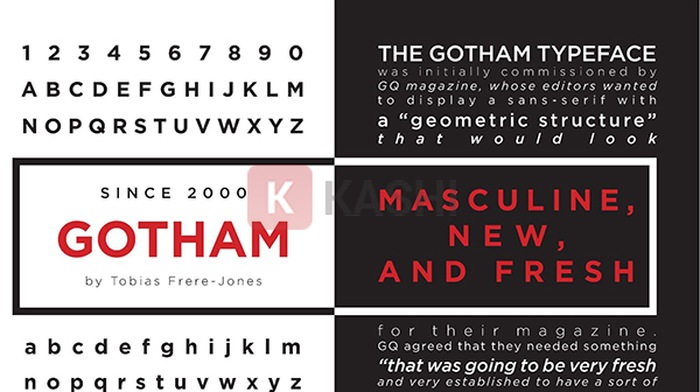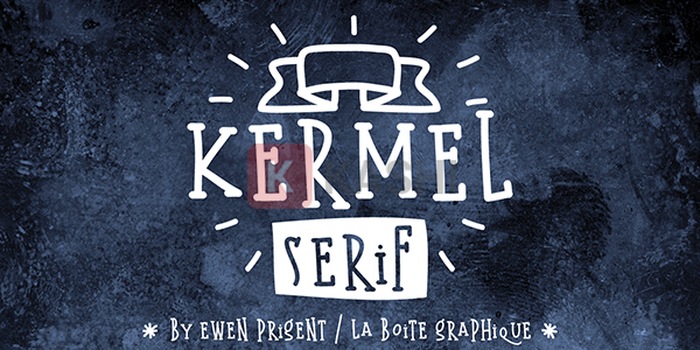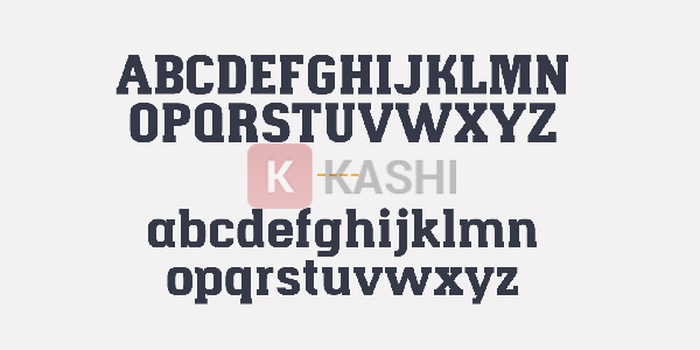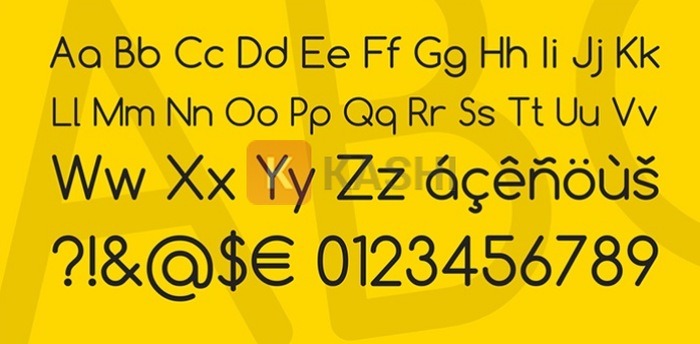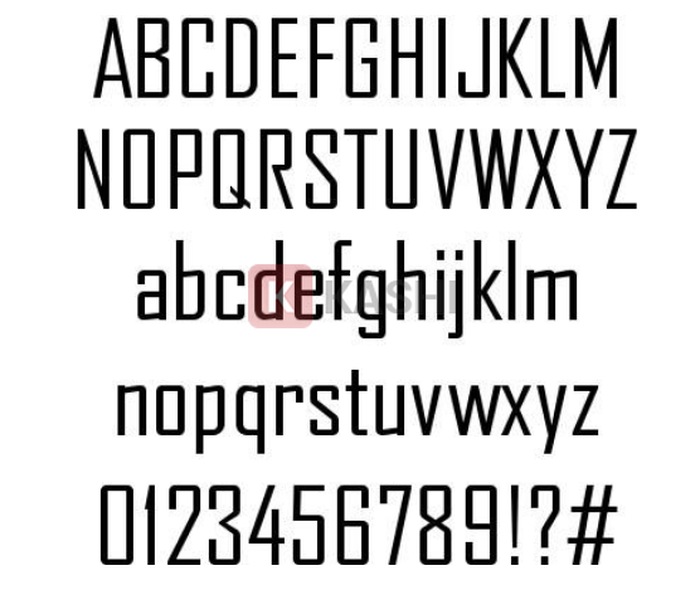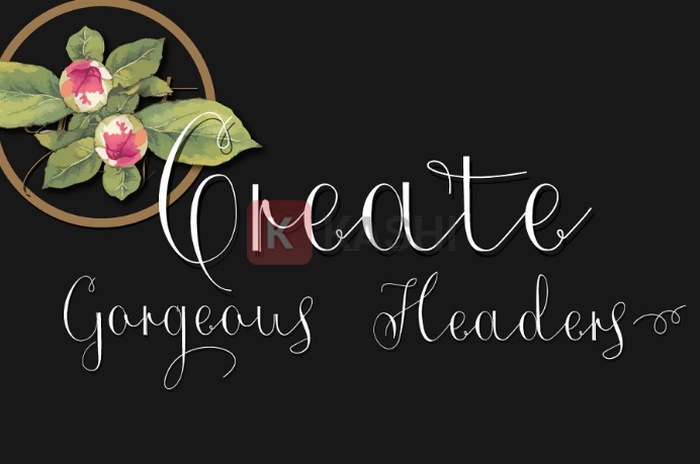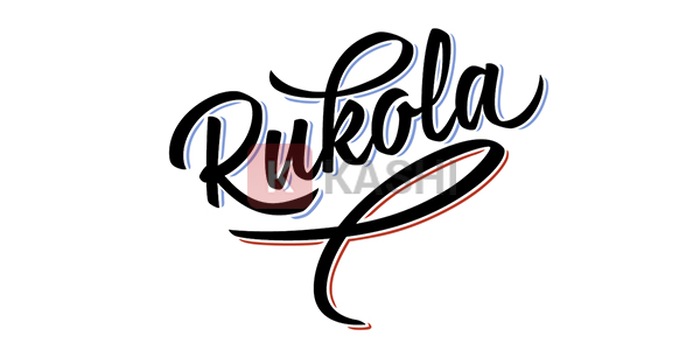
Top 10 Font Chữ Thiết Kế Logo Việt Hóa Đẹp Nhất 2025
Một logo chuyên nghiệp cần có hình ảnh, tên thương hiệu và slogan ấn tượng. Chọn đúng font chữ là yếu tố quyết định để logo thể hiện được bản sắc thương hiệu. Bài viết này sẽ giới thiệu 10 font chữ logo Việt hóa đẹp và miễn phí, giúp bạn tạo ra những thiết kế logo ấn tượng và chuyên nghiệp. Tất cả các font chữ đều tương thích với tiếng Việt và các bộ gõ phổ biến.
Font Chữ Logo Là Gì?
Font chữ logo là những font chữ được sử dụng để thiết kế logo, thể hiện bản sắc và cá tính của thương hiệu. Một logo ấn tượng sẽ giúp thu hút khách hàng và tạo dấu ấn riêng.
Việc lựa chọn font chữ phù hợp cho logo không hề đơn giản. Ngoài yếu tố dễ đọc, đơn giản, khả năng phóng to thu nhỏ mà không ảnh hưởng đến ý nghĩa, font chữ logo còn cần thể hiện tính hiện đại, sang trọng và khác biệt. Các font chữ thông thường khó đáp ứng được những yêu cầu này, do đó các nhà thiết kế luôn tìm kiếm những font chữ có nét độc đáo, gây ấn tượng mạnh với người xem.
Vậy đâu là những font chữ logo phù hợp? Hãy cùng khám phá top 10 font chữ logo Việt hóa tuyệt đẹp dưới đây.
Top 10 Font Chữ Logo Việt Hóa Miễn Phí
Dưới đây là bộ sưu tập 10 font chữ thiết kế logo tiếng Việt mới nhất 2025, được tuyển chọn kỹ lưỡng để giúp bạn tiết kiệm thời gian tìm kiếm.
1. Font Chữ Logo Hapna
Ra mắt năm 2013, Hapna (hay Hapna Slab Serif) đã trở nên quen thuộc với giới thiết kế nhờ tính ứng dụng cao với nhiều độ dày từ light đến black. Lấy cảm hứng từ bóng chày và các ấn phẩm thập niên 1950, Hapna mang đến sự khác biệt so với các font slab serif khác trên thị trường.
2. Font Chữ Gotham
Gotham, ra đời vào những năm 2000, lấy cảm hứng từ biển hiệu giữa thế kỷ 20 tại New York. Đây là font chữ không chân, cỡ chữ to, tròn và dễ đọc. Gotham đã được sử dụng rộng rãi, nổi bật nhất là trong chiến dịch tranh cử tổng thống của Barack Obama năm 2008.
3. Font Chữ Logo Kermel
Kermel là font chữ ngộ nghĩnh với độ cao các chữ cái khác nhau, không theo quy tắc cố định nhưng vẫn hài hòa. Phù hợp với thiết kế banner, poster sáng tạo.
4. Font Chữ Logo Roicamonta
Roicamonta là font chữ mềm mại, được ưa chuộng trong thiết kế logo mang phong cách nhẹ nhàng, lãng mạn. Font đã được Việt hóa và chia sẻ miễn phí.
5. Font Chữ Logo Agency FB
Agency FB phù hợp với logo mang phong cách công nghệ, kỹ thuật số, góc cạnh. Thích hợp cho các doanh nghiệp trong lĩnh vực công nghệ và thiết kế.
6. Font Chữ Logo Comfortaa
Comfortaa là font chữ bo tròn, mang đến cảm giác hiện đại, thu hút. Phù hợp cho thiết kế logo trong lĩnh vực công nghệ, phần mềm.
7. Font Chữ Logo Rukola
Rukola, thuộc dạng brush script, được sáng tạo bởi Nikola Giacintová. Với các ký tự đa dạng và tính năng swash alternate, opentype, Rukola tạo ra những nét chữ mượt mà, uyển chuyển. Phù hợp cho thiết kế bao bì, logo, tạp chí thời trang hoặc typography.